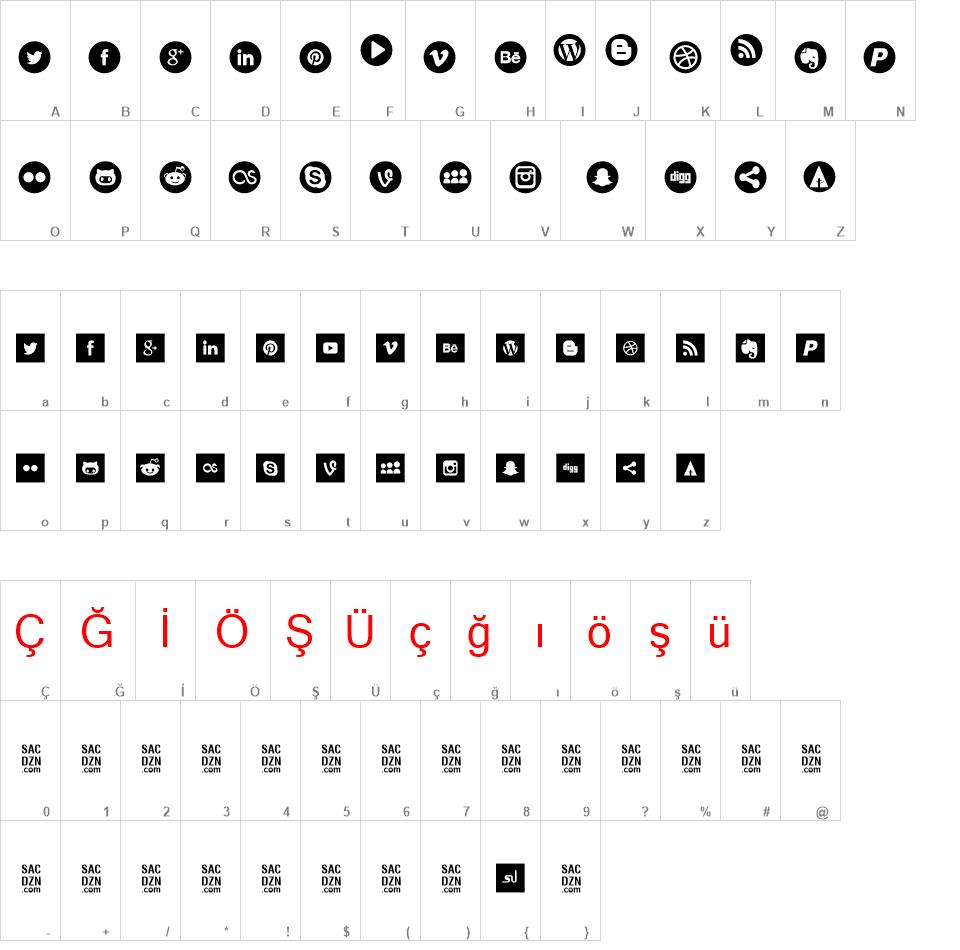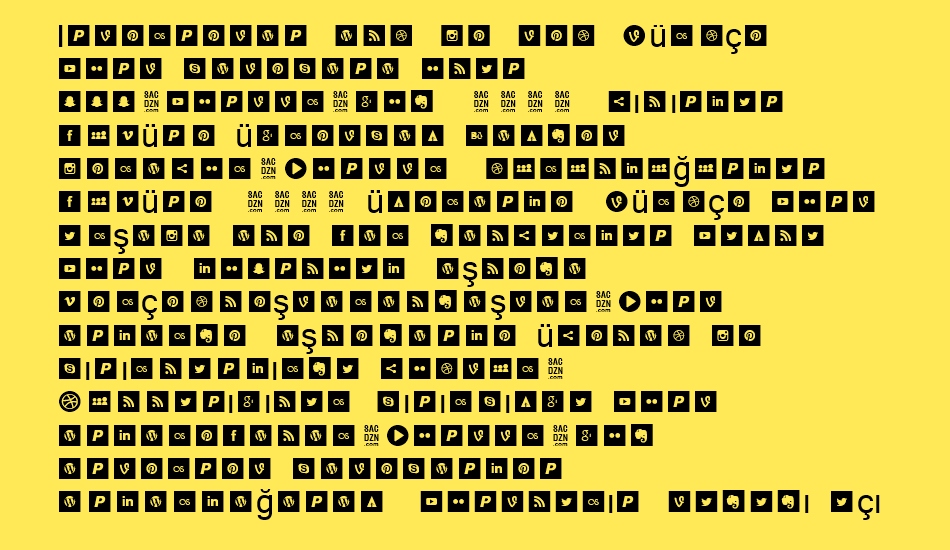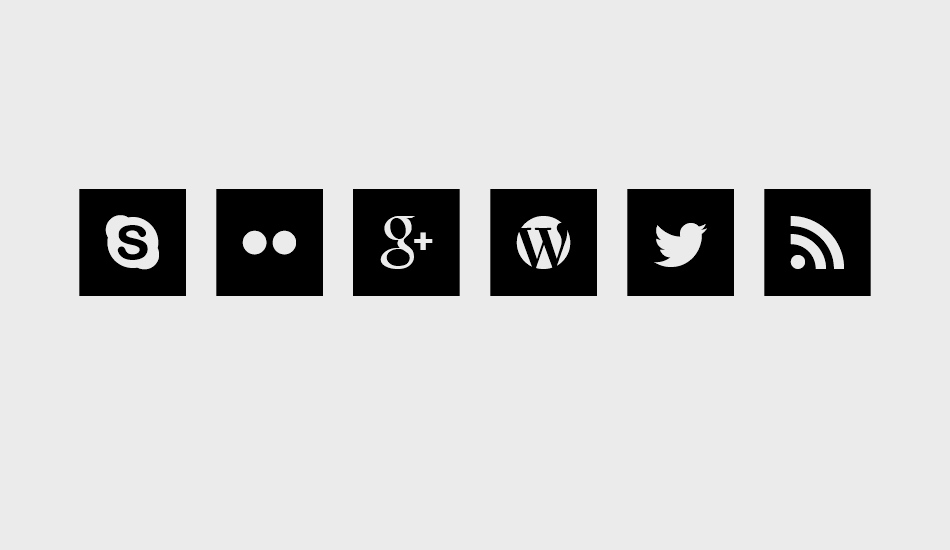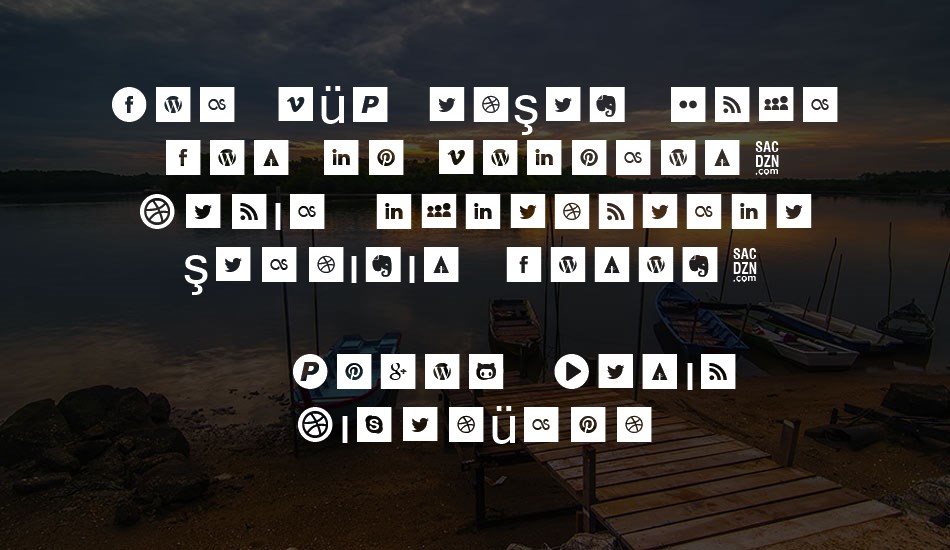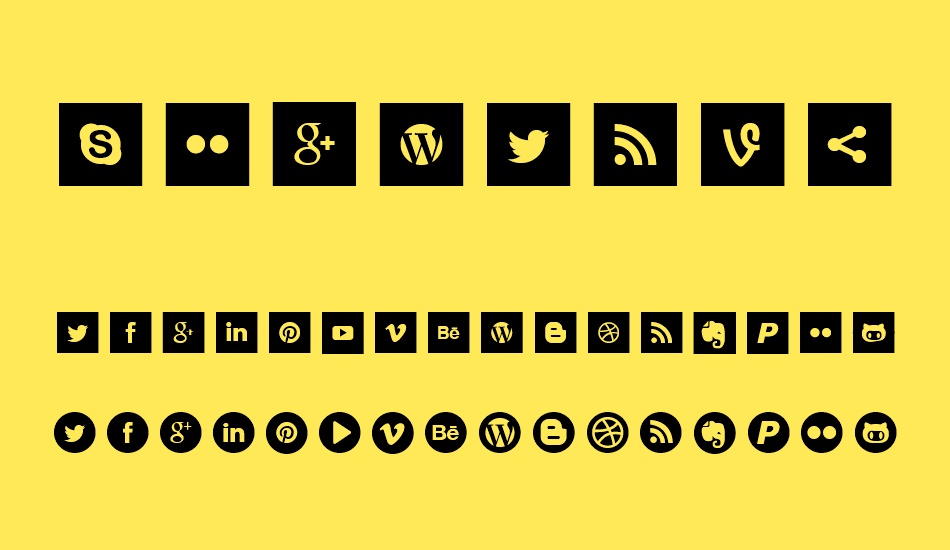
Social Type font
Sosyal medya iconları için font 100% free font,
ikonları istediğiniz kadar büyütün, istediğiniz kadar küçültün hiçbir şekilde bozulma olmaz.